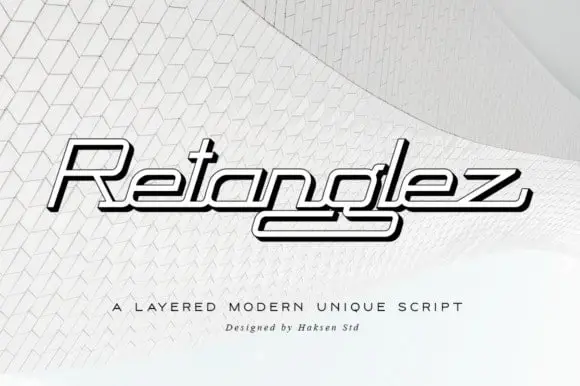
Retanglez Display Font
Retanglez Display Font é uma fonte de display experimental e futurista inspirada na ficção científica. Esta peça foi criada e compartilhada pelo designer sartstudio, celebrando formas geométricas abstratas em sua beleza inconfundível. Este design meticuloso destaca-se como um verdadeiro must-have para qualquer projeto de tipo moderno e vibrante. Composta por linhas finas, cores vibrantes e uma paleta de estilos únicos, Retanglez Display Font é a escolha perfeita para adicionar um toque único à sua identidade visual ou criar uma atmosfera futurista em suas publicações digitais.